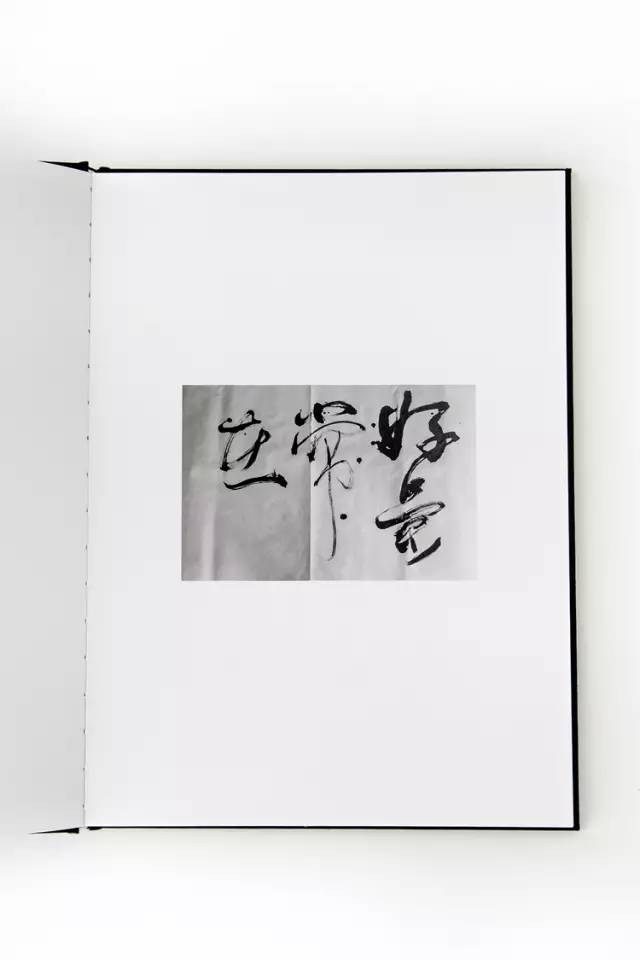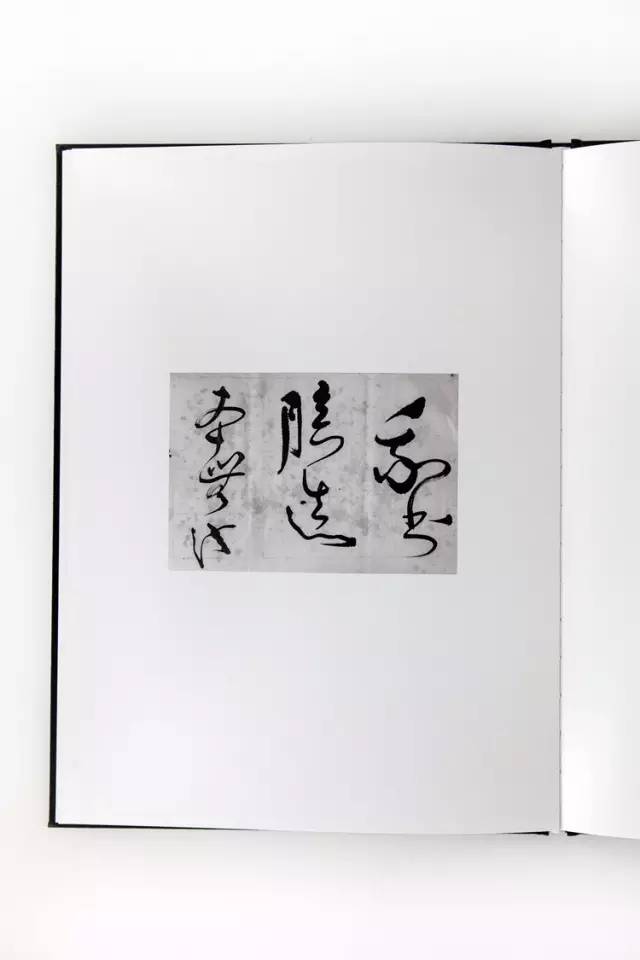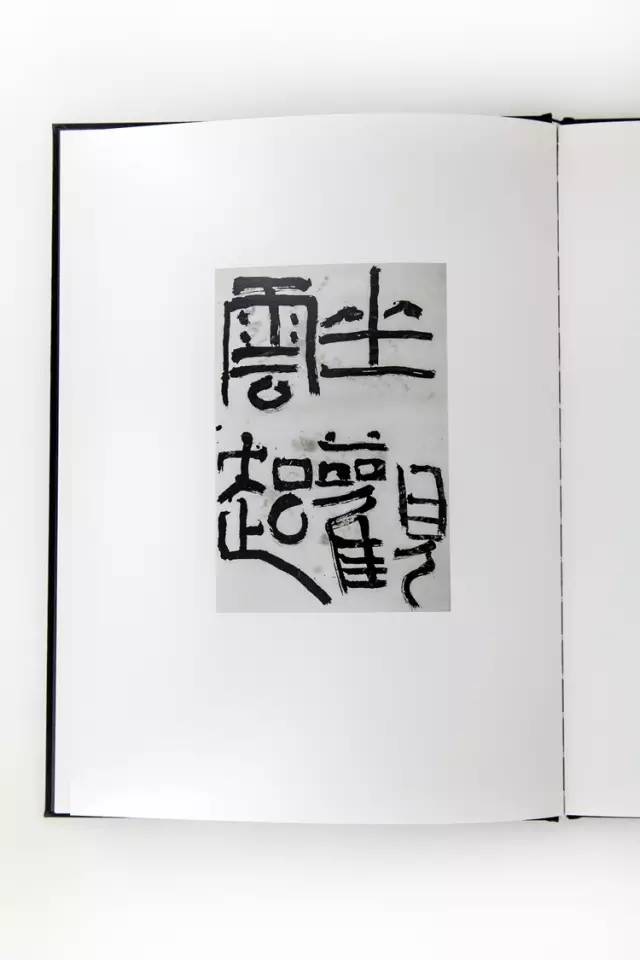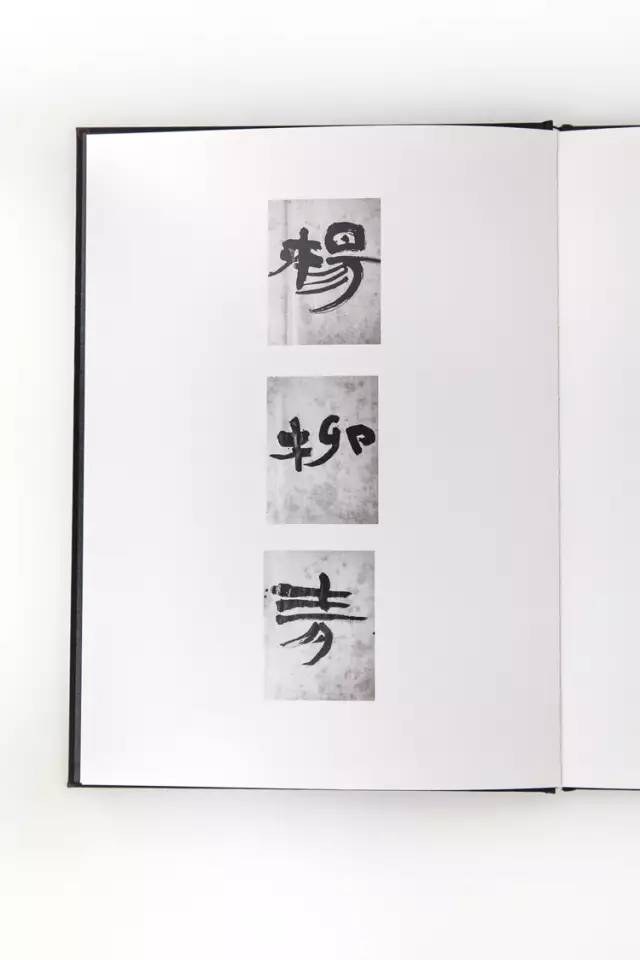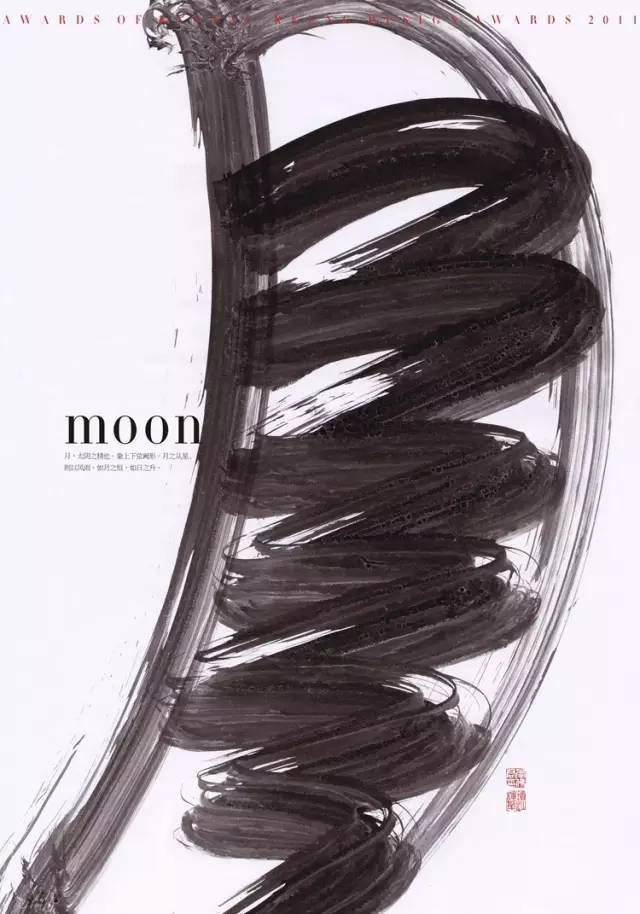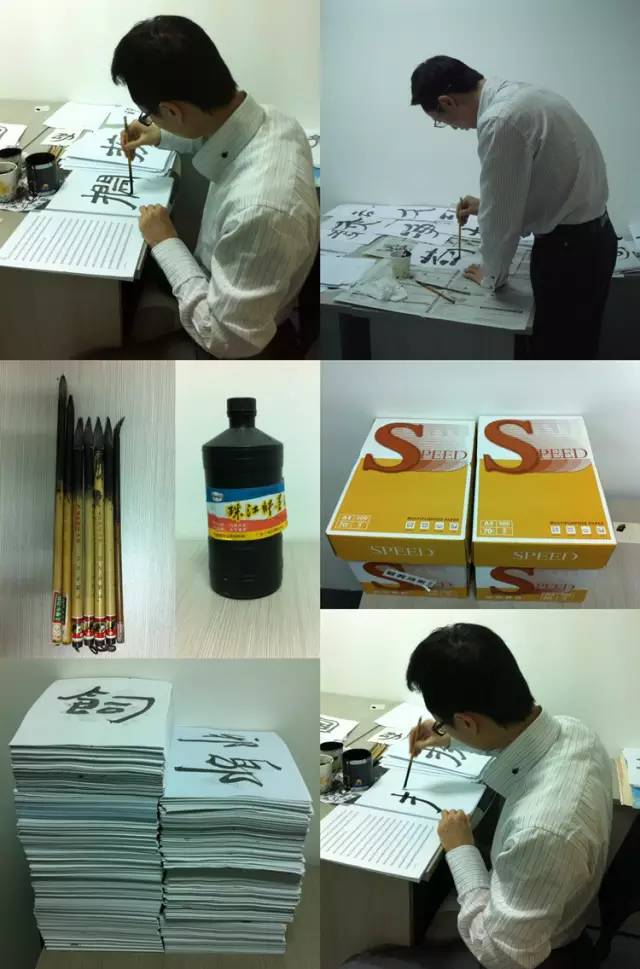
但行好事,莫问前程——李佛君
李佛君
彦辰设计(深圳)有限公司创办人/艺术设计总监。
国际平面设计协会联合会成员、深圳市平面设计协会会员。北大方正签约设计师。
多年来致力于品牌推广和企业形象设计工作,涉及文化艺术、快消费品、金融、房地产等众多行业,已为华润、怡宝、百事可乐、北大方正、深圳艺校、台铃、思摩尔等近百家著名企业机构及品牌提供常年策划及设计服务。
曾获台湾金点设计奖7项及入围2016年度最佳设计大奖、HKDA环球设计大奖5项、东京TDC年奖、GDC平面设计在中国7项、中国之星设计艺术大奖铜奖等12项、靳埭强设计奖8项、Hiii
Typography中英文字体设计大赛评审奖银奖等13项、华北设计艺术大展金奖等近百奖项,入选华沙国际海报展、文化部中国设计大展、深港设计双年展、亚洲平面设计三年展、亚太设计年鉴、中国设计年鉴、金蜂双年展等众多展览、赛事、年鉴。
来时的路
李佛君:我的祖籍江西,出生于世界脐橙之乡、宋城赣州。
9号西瓜:您是不是对历史很感兴趣?
李佛君:是的。
字体之路
9号西瓜:是什么原因让您产生设计字体的想法呢?
李佛君:我特别不希望大家给我贴上字体设计师的标签,因为字体不是我的全部,设计才是。既然你问到了字体,我就说说字体创作的一些经历吧。设计字体完全是因为喜欢。1993年夏天,父亲送我去系统学习书法,23年的墨池浸淫,书法对我的影响是深远的,那时不知道什么是字体。开始收藏邮票、老书、烟标、连环画、古币后,都被上面的文字深深吸引。后来我学习艺术设计专业,慢慢接触到广告、设计、版式这些内容,以手绘美术字完成作业,才慢慢产生字体的基本认知。再后来接触字体设计、了解字体设计。
2011年参加了GDC11(平面设计在中国)系列活动和广州的第一届汉字24时活动,接触到大量国内外字体设计师和热爱字体设计的朋友们,还加入了一个叫做“字体交换与鉴赏”的民间字体群体,这才令我的视野豁然开朗。
当年我创作了第一件字体设计(海报类)的作品:风花雪月。这个作品来源于2007年去大理旅游的经历,对当地的“风花雪月”四大景观念念不忘。
一次偶然,我洗毛笔时,毛笔上残留的墨水滴在桌边一张光滑的铜版纸上,呈现了很多漂亮的水墨肌理,让我有所触动,于是用这样的水墨顺手写下我时刻念想的“风花雪月”四个字,并且后来做了一个海报,并以此衍生了一系列的小产品:笔记本、文具、茶盒包装等。
雅昌发行的个人书法选
平时的涂鸦
大理“风花雪月”四大景(图片来自网络)
风花雪月海报
9号西瓜:关于字体设计,您是怎么汲取灵感的呢?
李佛君:设计不是天马行空,而是日积月累的能量呈现。1995年同学拆祖宅,从地里挖出一罐南宋古钱币,我当时用30元零花钱买下了这100多枚钱币。后来慢慢研究发现这些钱币上的文字叫九叠篆,是由北宋皇帝宋徽宗创立的一种笔画转折非常多的皇家御用字体。对这样焕发古典魅力的神秘文字痴迷了很多年。
2012年,字体小组成立三周年,我想结合现代的设计手法将作品做成古钱币的文字纹样,这时我就采用了九叠篆。
古钱币的文字纹样
字组三周年九叠篆海报
9号西瓜:是从什么时候开始设计字库呢?
李佛君:从事设计工作的前几年,发现可以用的书法字体非常少,比如“彦辰设计”这几个字,需要在前人书法作品里凑字,拼凑导致的结果是四个字的风格不同。从那个时期开始,我就想完成一套由设计师开发的适合设计使用的电脑字体。
2011年开始,我前后花了18个月时间,分别书写了9333个字符和7447个字符“彦辰清酒体”和“佛君包装体“,并由北大方正进行后期技术开发,终于实现了这个狂妄的想法。当然现在看来这两款字体都非常不成熟,有很多问题 。
这两套字体于2013年8月正式上市销售,目前被运用于商业设计领域,如小米、海尔、国美、苏宁、新华保险、安徽广电等都是这两套字体的用户。
从那以后我们陆续设计了17款书法类字库字形,即:彦辰系列的颜楷、新楷、欧楷、魏楷、新隶、新篆、灵飞笔意、朱熹刻宋、新颜、劲楷、千字文、谦篆、俊楷、心经、茶经、字经、赵楷等。
字库的开发档期无限延期,这些工作都是由我和团队一起,在商业设计工作的间隙、晚上、周末及假期里见缝插针、挤海绵里面的水般艰难完成的。有时大型商业设计项目遇到瓶颈,我会让同事们停下半天一天的,潜心做字。因为安静,因为专注,那些遇到的问题有时候迎刃而解、突然开悟。
方正佛君包装体字样
方正彦辰清酒体字样
彦辰欧楷字样
彦辰魏楷字样
- 朱熹刻宋字样 -
灵飞笔意字样
彦辰俊楷字样
9号西瓜:当时设计书法字库的情形是怎样?
李佛君:上班累了,在办公室写上几十或几百个,权当休息。记得当时买了几十箱500张一包的A4纸,前后完全写坏写残的毛笔及墨水记不清用了多少、写过的字稿叠加起来超过了我的身高(搬办公室的时丢弃的字稿就有20多箱)。因为整箱整箱地买纸墨,送货员一度以为我们是文具电商。
写完字稿后用自动扫描仪,边做边导入、设计修正,最终制成AI文件提交给方正进行技术开发。写字稿持续了大概9个月,加上后期的设计修正,整个项目耗时18个月。
我是工作间隙和业余来做这事,前后书写了一万多张字稿,有好几次,因为书写的时间不一,写的效果不一样,又重新写过,这样的字数不计其数。方正进行后期编排的时候,发现有些字不符合国家书写规范或有技术瑕疵,让我重新书写。这样的书写量,要不是因为爱好,是很难持续完成和落地的。过程虽然很艰辛、但是充满激情和憧憬。
书写两套字稿时候的情景
9号西瓜:电脑字库和传统书法行文的逻辑不同,您在设计过程中有什么取舍呢?
李佛君:传统书法的运笔和布局出发点基于艺术欣赏、个人风格,电脑字库考虑的是商业设计的实际用途和场景需要,比如阅读体验、识别效果等等。书法讲究行云流水、笔墨质感,在设计字库作品中除了考虑以上因素外,还需要关注字的比例和距离,甚至有时不能出现相连贯的东西。写每个字的时候,我都是独立当成一个字写在A4纸上。
- 每个字我都独立书写 -
9号西瓜:是否有遇到字体侵权事件,怎么处理?
李佛君:当然。有大量未经授权和购买的企业及个人侵权使用,有的是企业主、也有设计师、设计公司、广告公司。有明目张胆地的使用,被我发现、被方正发现或被热心的朋友、同行发现的,方正的法务团队很强大很专业,这些事务都是他们在维权、处理。
9号西瓜:您是怎么看待西方字体设计与东方字体设计,甚至很多设计师在追崇西方的呢?
李佛君:论东西方文化各有千秋,并不能一定说谁好谁坏。老祖宗留下来的东西,并不能全部说好。取其精华去其糟粕,也许比较科学可行一点。我也欣赏北欧的极简的视觉语言,但是我更加喜欢清灵雅致的东方美学,尤其是宋代和明代两个朝代,在艺术造诣上是非常高的。
西湖雅集标志
丝瓷茶艺标志
周小雨个人形象
墨界善意
字组标志
彦辰设计标志
公司环境
9号西瓜:现在团队人数主要维持在多少人呢?
李佛君:近几年我一直将团队的人数保持在10人左右,争取保持精简和高效的工作状态。当然随着业务需要,我们也持续稳步的扩张团队。
公司上下班不打卡,我的房间不上锁,即使是个人私藏的各类古籍古玩藏品都是完全对大家开放的,主张open的环境。深圳及周边城市的赛事、展览、讲座、沙龙等专业交流活动,只要没有特别的工作冲突,我都安排全公司参与,让大家可以开拓眼界。比如前阵子蒙纳字库在深圳的分享会,我们就是倾巢出动去学习,大家甚至为了占个座位连午饭都来不及吃。还有今年三月份的公司旅游,我们安排了前往香港观看刘小康设计三十年展,次日我们则在香港海洋公园畅玩了一天,我始终相信劳逸结合、寓教于乐。再会工作也要学会休息和放松,这样才可能走得更久更远。
偶尔我出差几天不在公司,甚至会意外发现同事的工作效率比我在的时候还好,这得益于平时的和大家的充分交流、分工明确、健全机制的建立。如果一个团队突然有人离岗工作就瘫痪的话,那就很糟糕了。
公司环境
提醒大家时刻反省的《君子九思》
各类收藏及各类书籍完全开放
节日传播画面
9号西瓜:您现在侧重于培养团队哪一方面的能力呢,是字体设计还是商业上的?
李佛君:因人制宜。我的目标是培养全面发展的人,不只局限在某一方面。专业设计很重要,但是慎密的思维方式、良好的行为习惯都会对工作有很大促进和影响。所以,我从来以培养综合性人才为最高目标,实现他们的个人价值,他们未来甚至可以独当一面和开创更高更强的事业局面。目前公司的主管和资深设计师都是从一线的普通平面设计师培养、成长起来的。他们进入彦辰之初,可能仅会一两项基本的平面设计技能,比如标志、字体、效果图、排版之类,但是经过多年的培养和锻炼、塑造,如今他们已经可以从容应对客户对接、业务跟进、基础的团队管理、商业空间的设计、展览设计等多项技能。
另外我特别想说的是,我极为抵制标题写:个人简历、个人作品这类没有任何署名或个人信息的应聘邮件,因为一个连基本个人信息都不善整理传播、不能换位思考的人,难以想象怎可有缜密的工作思维做好工作?不去想象一下HR将收到多少邮件,如何识别你记住你?之前我还专门写过一篇题目为《设计师应聘指南》的小文章,同学们可以去看看,怎样培养慎密的工作思维和良好的行为习惯,从找工作开始。
北京大学出版社《中国思想之渊源》装帧设计
9号西瓜:您是怎么看待早几年的和这几年的新人设计师之间的区别呢?
李佛君:大师都好相处,为人谦卑。他们给我们树立了接人待物、谦虚低调的优秀典范,值得我们学习。现在的85后、90后非常有性格,敢说敢做,这是好事,有时也会欠妥。现在的时代需要个性
,但是也需要一定的规则去约束,能在有限的条件下创造无限的可能、能在平凡处创造不平凡才是能力、才是能量。商业板块的作品,设计是为了解决实际问题,需要从用户、从市场等多方面为导向去开展。只有进行艺术创作才可能尽可能展示自我的一面。
每个月几百封的求职信中,我发现越来越多的年轻人并不是看中福利和薪水这些传统价值观,更多的关注这个工作的平台是否适合自己、是否喜欢这份工作。很多求职的设计师认为在这个团队里做字体设计是一件很有趣、很了不起的事情,不在乎公司福利,在乎平台。我则往往会告诉他们,我们不是仅仅只做字体设计的,彦辰是一家综合性的商业设计公司,字体设计仅仅是业务板块之一,充其量不足三分之一的份额而已,希望你们做好心理准备,并且我也会将大家培养为全方面的人才,而不仅仅是一名字体设计师。
这就是新一代设计师以追求自我乐趣的就业观念。这与老一辈设计师可能有不太一样的地方,这也是时代和社会的进步。
五十十五澳门回归15年海报
中国设计年鉴9海报
跨界之路
9号西瓜:现在公司的经营模块划分为几块呢?
李佛君:总体分三大板块:第一是占比过半的企业和品牌的形象设计、推广这类纯商业项目,服务的对象是以快销品、金融、文化产业、地产、政府机构等,例如我们近年一直担任华润怡宝华南地区的品牌推广设计工作,深圳艺术学校的视觉形象系统和导视设计,音符葡萄酒的品牌推广及包装设计,台铃电动车的品牌推广设计、国内电子烟龙头企业思摩尔视觉系统设计;第二个版块是字体相关的业务板块,包括字体设计和字库开发,如和方正等合作开发字库产品,目前上市的有彦辰清酒体和佛君包装体,也有正在开发中的各类字库产品,甚至还会在不久的有方正彦辰雅黑等正文字库上市;第三个版块是文创产品,现在还做的不太多,目前和字在、山田土、慢物质等文创品牌联动合作,也有完全自主开发的文创品牌,如推崇汉晋美学的“砖家”品牌等。
华润怡宝的品牌推广及设计
华润怡宝:“大学不一样”开学季推广
华润怡宝:深圳马拉松战衣
华润怡宝:龙舟赛品牌推广
华润怡宝:微信节日推广
深圳艺术学校
从2015年开始为深圳艺术学校提供形象整合升级,目前仍未完成。李云迪的母校:深圳艺术学校享誉国际的专业是钢琴,所以整个校园的视觉设计都以黑白琴键为核心进行延展设计,并将寓意年轻活力和展现不同专业活力的多种色彩来区分不同楼宇、建筑和进行功能区分。
9号西瓜:现在文创产品迅速发展,一个是由于国家推崇,很多设计师也跨界设计产品,您怎么看?
李佛君:希望不是为创作而创作的。台北故宫的文创产品古为今用转化运用得很好,将把传统文化通过现在的视角进行转化,同时富有趣味,变成与老百姓息息相关的物件,增加了生活情趣,提升存在价值。
风花雪月措铜茶具(with慢物质)
字在《风花雪月》笔记本
9号西瓜:介绍下您和字在合作的文创产品吧~
李佛君:和“字在”合作,目前推出了多个产品。初心就有两个系列的产品。
第一个系列大师系列。很多产品都着眼于开发大师成熟的作品,我想用一组产品剖析揭露大师早期,这些早期作品正是奠定他未来艺术成就的基础。所以选取达芬奇、毕加索、莫奈、梵高、塞尚等大师早期没有形成明显个人风格和体系的作品,将产品命名为“初心”,传达给大众的的理念是“原来大师也是这样过来的,我可以勇敢去描绘自己的蓝图”。一是说大师的初心,二是描画作品的初心。
第二个系列儿童系列。我看到幼儿园小朋友们的涂鸦画,天真无邪,特别有感触,希望将他们的画作融入产品,引导人们关注自己善意的初心。
此外还有《风花雪月》笔记本、《美意延年》利是封、《猴赛雷》利是封等产品。
字在中国品牌VI优化
字在《初心-大师早期作品系列》
字在《猴赛雷》利是封
9号西瓜:您还做了哪些产品和领域的跨界尝试呢?
李佛君:整合现有的资源是有价值的一件事情。之前提到的“风花雪月”已经具备市场影响力,于是我将其做成了本子。合作方支付设计费,帮我们生产实现为产品并且上市推广销售,多方多赢。
还有一个产品是利是封。春节发利是封,大多数人只关注里面有多少钱,并没有关注到红包的含义是对长辈对晚辈的祝福。于是我设计了6枚利是封,4枚是给小朋友的“你真棒、快乐100、快高长大等”。2枚是给长辈的“福禄寿喜、美意延年”。这个思考是基于传统文化,作为对当下的文化缺憾的补偿。
我还有一个跨界创作,就是为深圳地铁第三期9号线的梅景站创作了艺术墙。我以2011年创作的《大象无形》海报运用于梅景站艺术墙上,并对细节进行调整。这次的创作是近年跨界动作最大的,加上超越常规的制作难度,是一次很不平凡的经历。画面上的花朵分了32个层级、27种色彩,用5毫米厚度的阳极铝板切割成形,再用汽车烤漆级的工艺将这些复杂的层次进行高温喷涂和烤漆,最后进行超高难度的组装和安装,整体工程历时三个月才完全完成。虽然困难重重,能给公共艺术空间带来一点点新意也是很美好的一次体验。这也是设计师作为社会成员一份子感到的一份责任与荣耀。
字在-羊年利是封
《大象无形》海报
《美林》大型公共空间艺术装置
亦古亦新
9号西瓜:别人大多是怎么称呼您的?br />
李佛君:称呼我为老师的比较多。目前的工作不仅仅在视觉和平面上,也有文创产品,甚至有品牌顾问、企业培训。我希望自己可以并不局限于某一称谓,希望个人和公司都可以多元化发展。
9号西瓜:您觉得自己一个怎样的设计师?
李佛君:亦古亦新。我是双子座,有双重性格,亦动亦静。喜欢古典的传统文化,也接受新锐年轻的当代时尚。
9号西瓜:您觉得设计师最核心的素质是?
李佛君:敬业的态度。我可以容忍不懂得做设计,但是不能容忍拖沓懒散、推卸敷衍的态度。
李佛君:这个问题很大,估计再讲一天也讲不完。记得有次韩国海报展的主题是“设计师应该为社会做些什么”。我认为设计应该要为优化生活而存在,并且产生社会价值、商业价值。
9号西瓜:设计给你最大的成就是?
李佛君:安于此道,安家乐业。
9号西瓜:这么多年的设计经历,有什么感想或收获吗?
李佛君:刻心怀感恩。到12月28日,彦辰创立7周年了。这些年来,每一步成长和进步,都离不开家人亲人的鼎力支持,特别是在外企担任要职的太太,在繁忙的工作之余,包揽几乎全部家庭和女儿的事务,解决我的后顾之忧,还兼顾彦辰的外务工作。毫不夸张的说,没有太太的给力,我不可能安心工作,也根本不可能有我的今天、彦辰的今天。所以我想把能够给予家庭的时光都用好用尽,因为我花在家事和女儿身上再多的时间,在太太面前都不值一提。现在这点我还做得不够好,还需要努力。
还有就是特别感谢客户及合作伙伴们、同事们的一路同行、扶持、助力。
有几点收获,这些比获奖和赚钱重要百倍:
一是平时的积累和持续学习特别重要。当我们吃九个小笼包吃不饱,吃到第十个才饱,但不可以说只吃第十个包子就可以吃饱,这需要积累。对一件事的持续思考和发力才有可能有成果。
二是永怀进取心。有一句特别想分享的话,来自我的引路人王粤飞老师,他说“种瓜得瓜种豆得豆,虽然种了不一定有收成,但是如果不种,就一定没有收成。”这句话深刻影响着我,我们需要一直怀抱一颗谦卑的心,去播种、去耕耘,才有可能有所成绩。
曾国藩有云:只问耕耘,莫问收获。这句话告诫我们,不要只想着收获,若不耕耘,怎么收获,就像大树一样,养的深根,日后才能枝繁叶茂。只有时刻警醒才能时刻精进。
女儿在我的影响下喜欢涂鸦
我们爷俩
9号西瓜:会做多久的设计呢?
李佛君:活到老学到老、做到老,也不确定哪天会心生倦意。
早点来深圳
9号西瓜:您听歌有什么倾向吗?喜欢看什么类型的电影?
李佛君:一种是美国民谣和纯音乐,如班得瑞,另一种是beyond式摇滚,最喜欢的歌曲是Alan Jackson的《remember when》和beyond《海阔天空》。这些都是经典。
基本上各种类型的电影都看,尤其喜欢《阿甘正传》。但不喜欢阴暗、血腥、魔幻类型的电影。
9号西瓜:有无对您最具启发的书呢?
李佛君:必须说是由王序老师主编、中国青年出版社1999年出版的《陈幼坚:平面设计师之设计历程》,可以说这本书是我的设计启蒙书。当年我还在上大学,我看到陈幼坚老师从花花绿绿的水果包装纸进而对设计产生浓厚兴趣开始,之后进入当时以外国人为主的广告公司工作,不嫌弃苦累从底层做起、学到很多东西,再到后来开办设计公司、再到后来创作了很多极具代表性的设计作品,这些历程都对我产生了深远的影响,也让我萌发了也要像大师一样热爱并一直坚持走设计之路的决心。
另外我要特别提及一个人,就是我的父亲。在我十岁那年,父亲拿回来两本空白的集邮册,给我和弟弟一人一本,虽然当时并不懂集邮,但因为有了集邮册,就开始有意无意的收集邮票,到后来收集烟标、古币、连环画、各类古玩等,从此一发不可收拾,也可以说是花花绿绿的邮票打开了我的艺术眼界,在方寸间我找到了属于自己的人生方向。那本集邮册也可以算是一本影响了我的“书”。
李佛君:一是把设计公司经营的更加成熟。第二是积极关注设计教育、投身推动设计教育的工作。第三是争取晚年成为职业书法家。